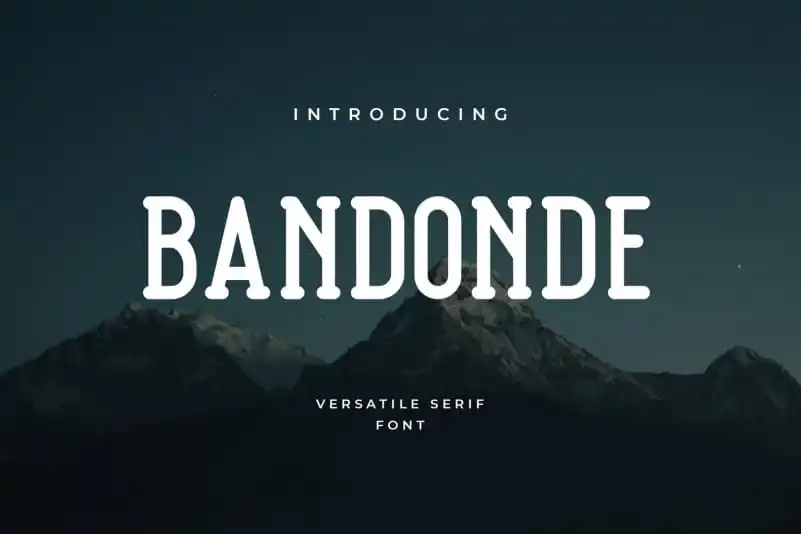
Bandonde Serif Font é uma elegante tipografia multifunção que combina características modernas e sofisticadas com nuances serifais tradicionais. Criada pelo designer UI Creative, esta font pertence à família de tipo serifado ornamental, oferecendo um estilo firme com nuances refinadas. A fonte inclui ligaturas, alternâncias estilísticas e swashes que podem ser personalizadas, tornando-a ideal para aplicar em logotipos e títulos, designs bonitos e conteúdo, tanto grandes quanto pequenos, adaptando-se perfeitamente a diversos ambientes gráficos. Suas letras maiúsculas e minúsculas elegantes se destacam quando combinadas com seu rósti arredondado de estilo vintage ou retrô, além de serem adequadas para diversas culturas como os amantes das motocicletas, tendências rockabilly e estilos clássicos. Ideal para quem busca um toque de sofisticação em design impresso, digital ou digital signage, a Bandonde Serif Font é perfeita para criar uma experiência visual única e intrigante. Esta fonte não só adiciona um toque especial aos seus projetos gráficos, mas também oferece uma maneira criativa e estilosa de expressar sua identidade. Com seu design original e versátil, a Bandonde Serif Font pode ajudá-lo a destacar-se em uma multidão de designs digitais ou impressos, proporcionando um visual diferenciado que ressalta sua criatividade e estilo único.